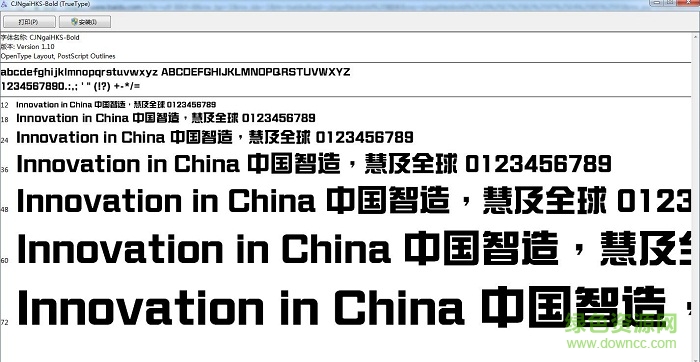
cjngaihksbold 粗體是一款西方美術(shù)字體,這款字體同時(shí)結(jié)合了黑體和宋體的特點(diǎn),線條流暢,筆畫(huà)粗,易認(rèn)易識(shí),大氣又不失趣味,一般用在廣告設(shè)計(jì)、網(wǎng)頁(yè)設(shè)計(jì)等方面,歡迎大家免費(fèi)下載!